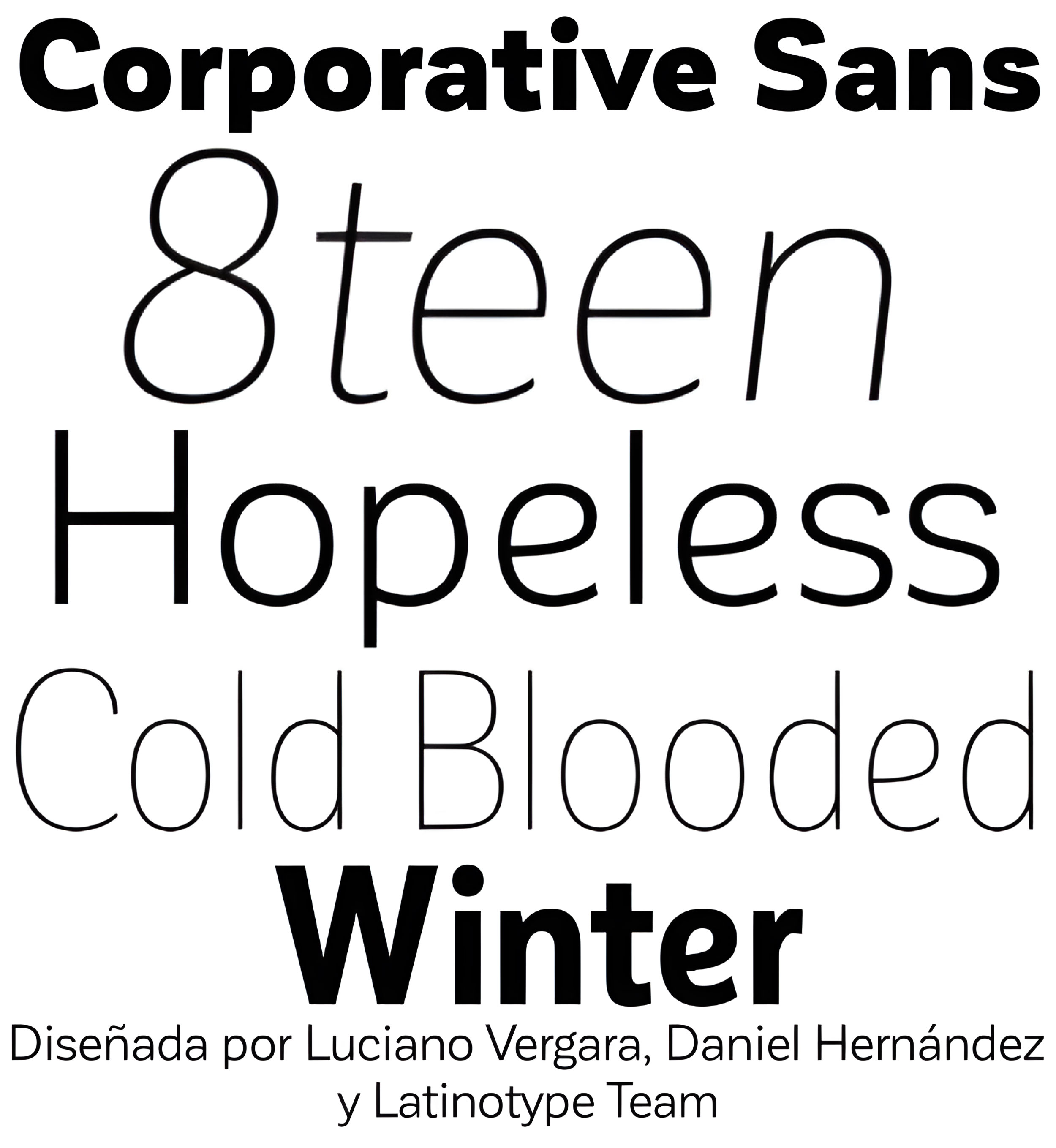
| Año | 2015 |
| Créditos | Luciano Vergara, Daniel Hernández |
| Descripción | El tipo de letra Corporative Sans ha sido desarrollado por Latinotype Team. Corporative Sans es la nueva versión de Corporativo. Esta fuente tiene una marcada personalidad y rasgos distintivos, lo que la hace adecuada para ser utilizada en tamaños de texto grandes. Al ser una fuente condensada, también puede utilizarse en tamaños más pequeños. Corporative incluye el conjunto estándar de 350 caracteres de Latinotype, lo que permite utilizar la fuente en 128 idiomas diferentes. Corporative ofrece a los usuarios una amplia gama de caracteres, pesos y anchuras para cada proyecto. Combinando distintas variantes, los diseñadores pueden conseguir los mejores resultados. La familia consta de 64 fuentes: una familia básica que incluye 8 pesos más cursiva, una familia alternativa de 8 pesos con cursiva a juego y 2 familias condensadas, una normal y otra alternativa, ambas con cursiva. Latinotype ha incorporado nuevas caras a su equipo. El equipo de Latinotype se compone ahora de: Rodrigo Fuenzalida, César Araya, Bruno Jara, Luciano Vergara y Daniel Hernández. Corporative fue creada por Latinotype Team y desarrollada por Javier Quintana, Rodrigo Fuenzalida y César Araya, bajo la supervisión de Luciano Vergara y Daniel Hernández. |
| Familia(s) | Corporative Sans |
| Estudio | Latinotype |